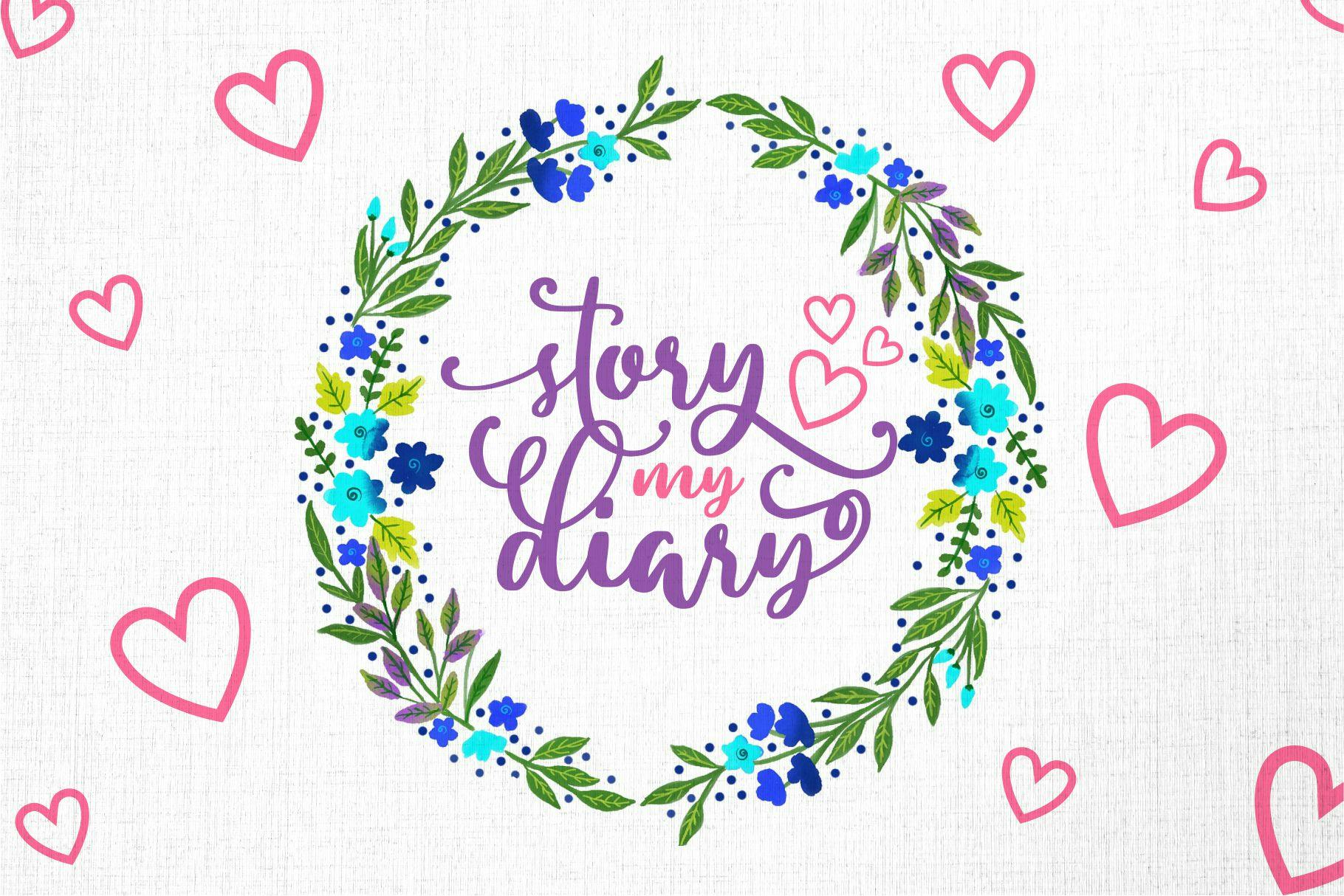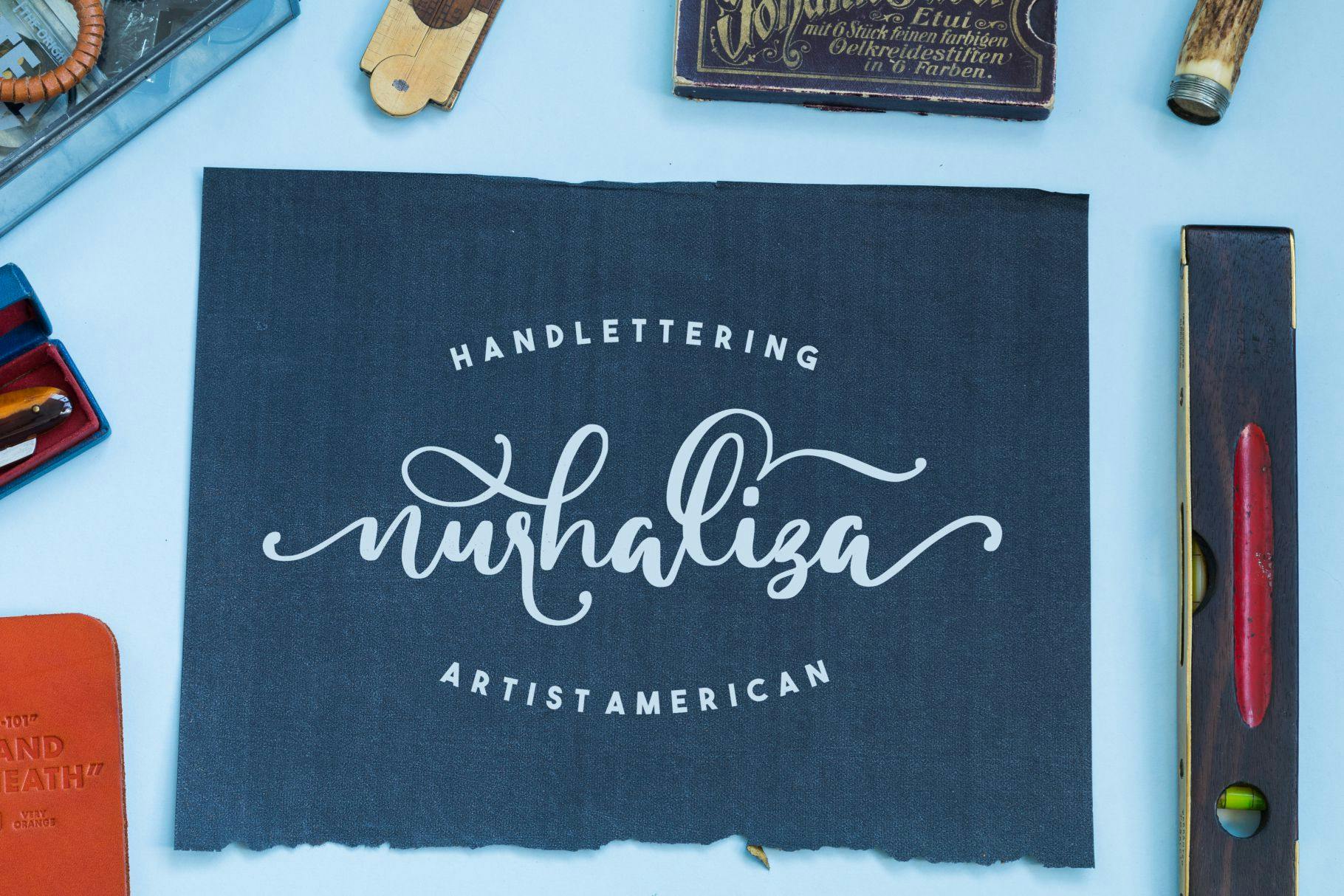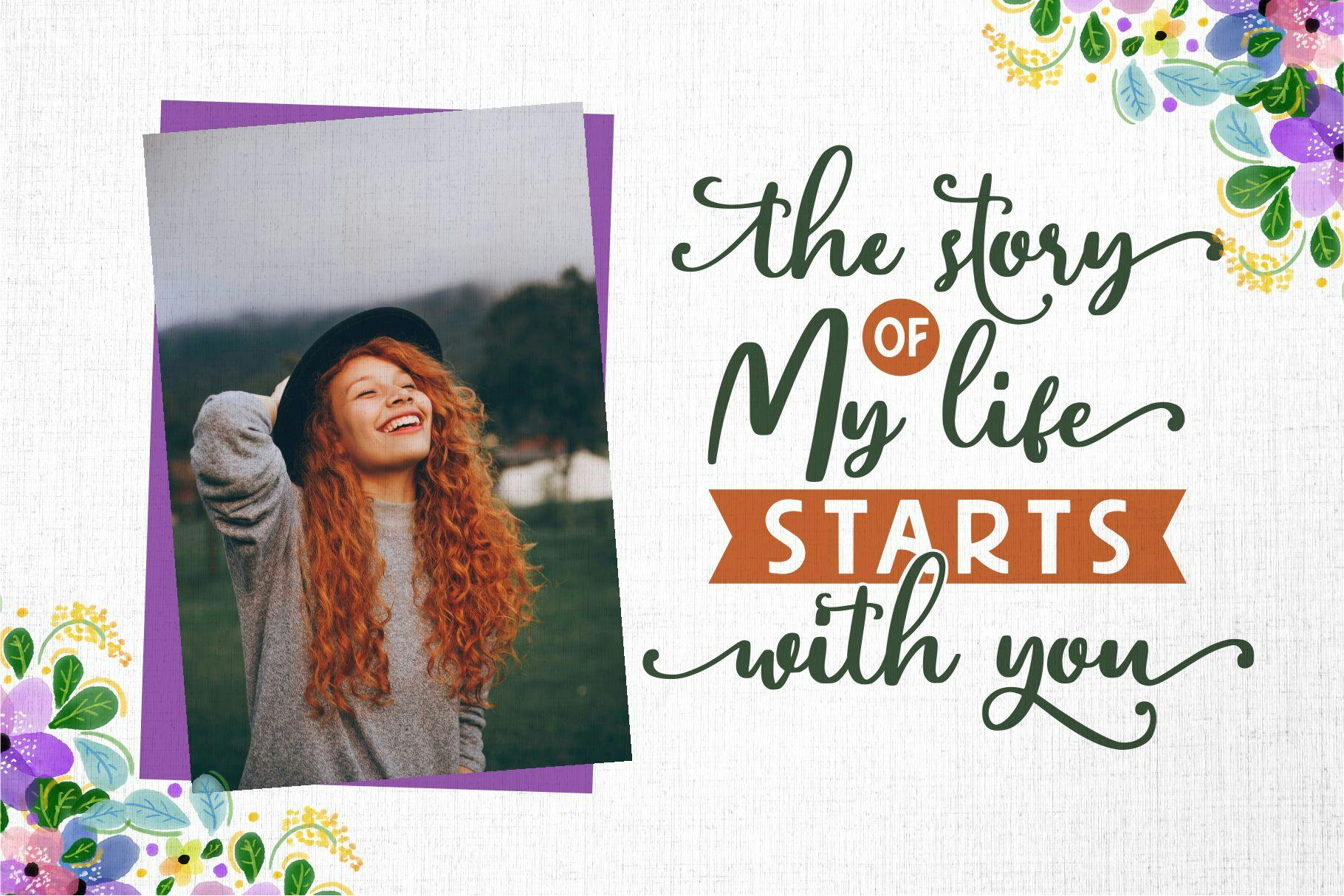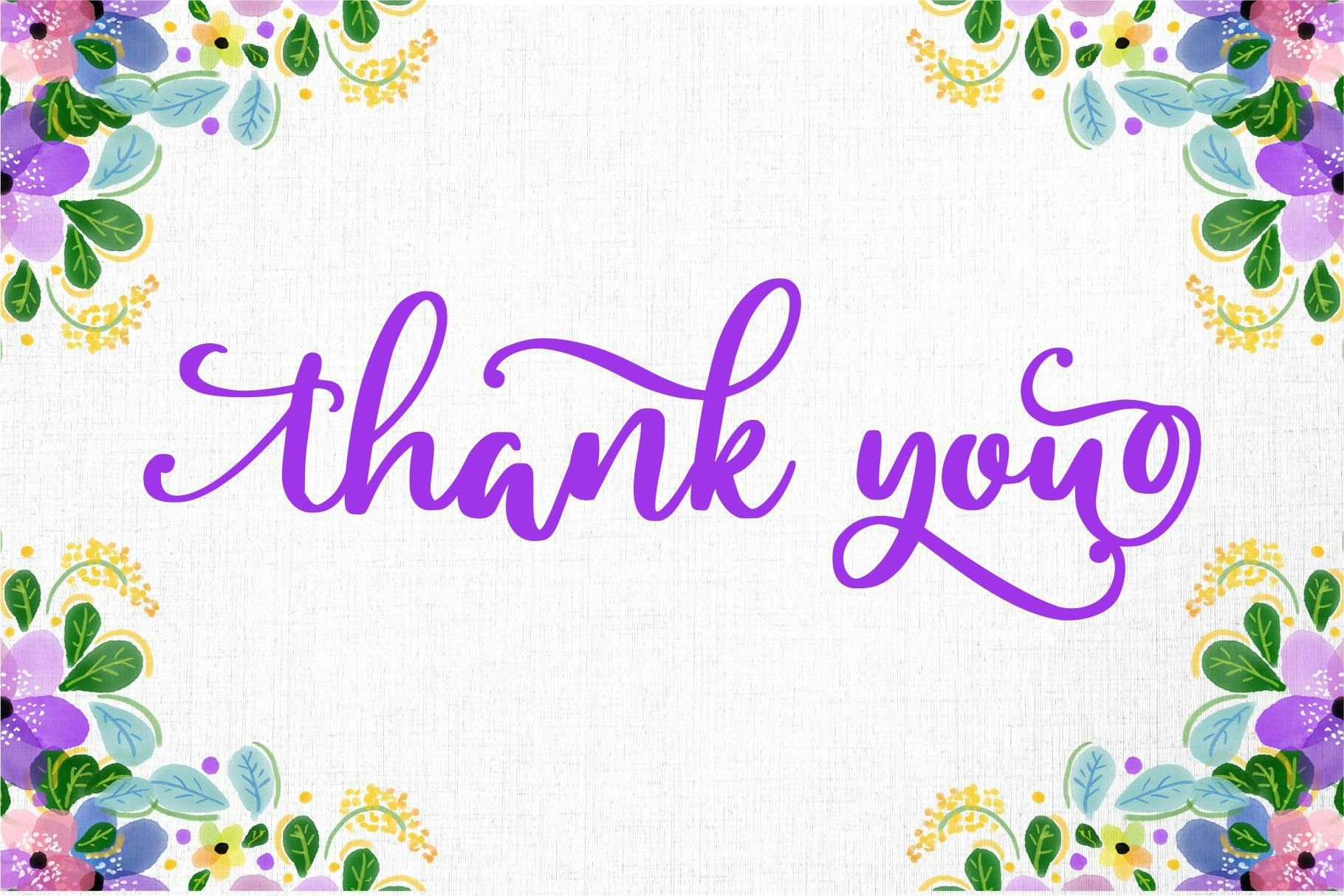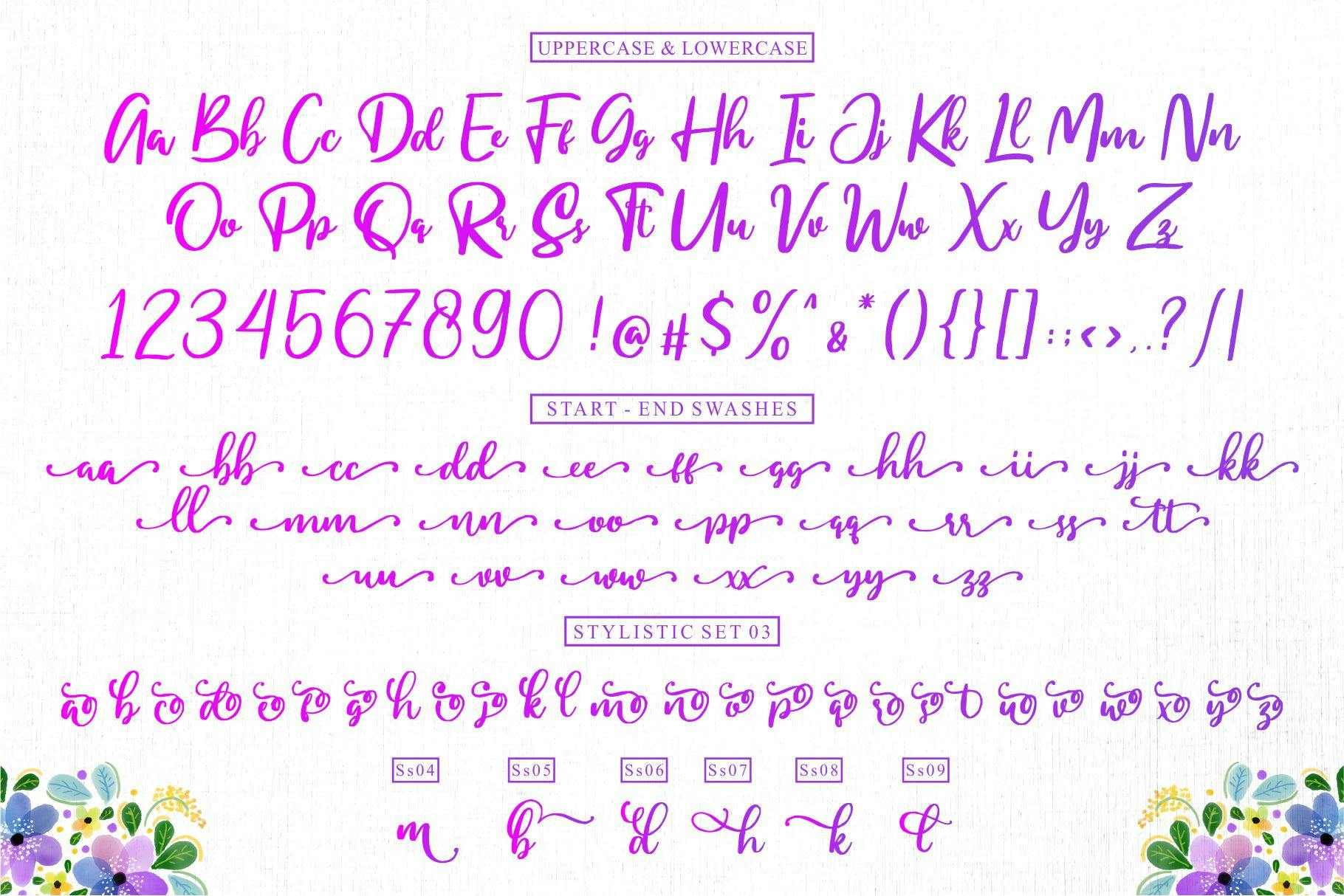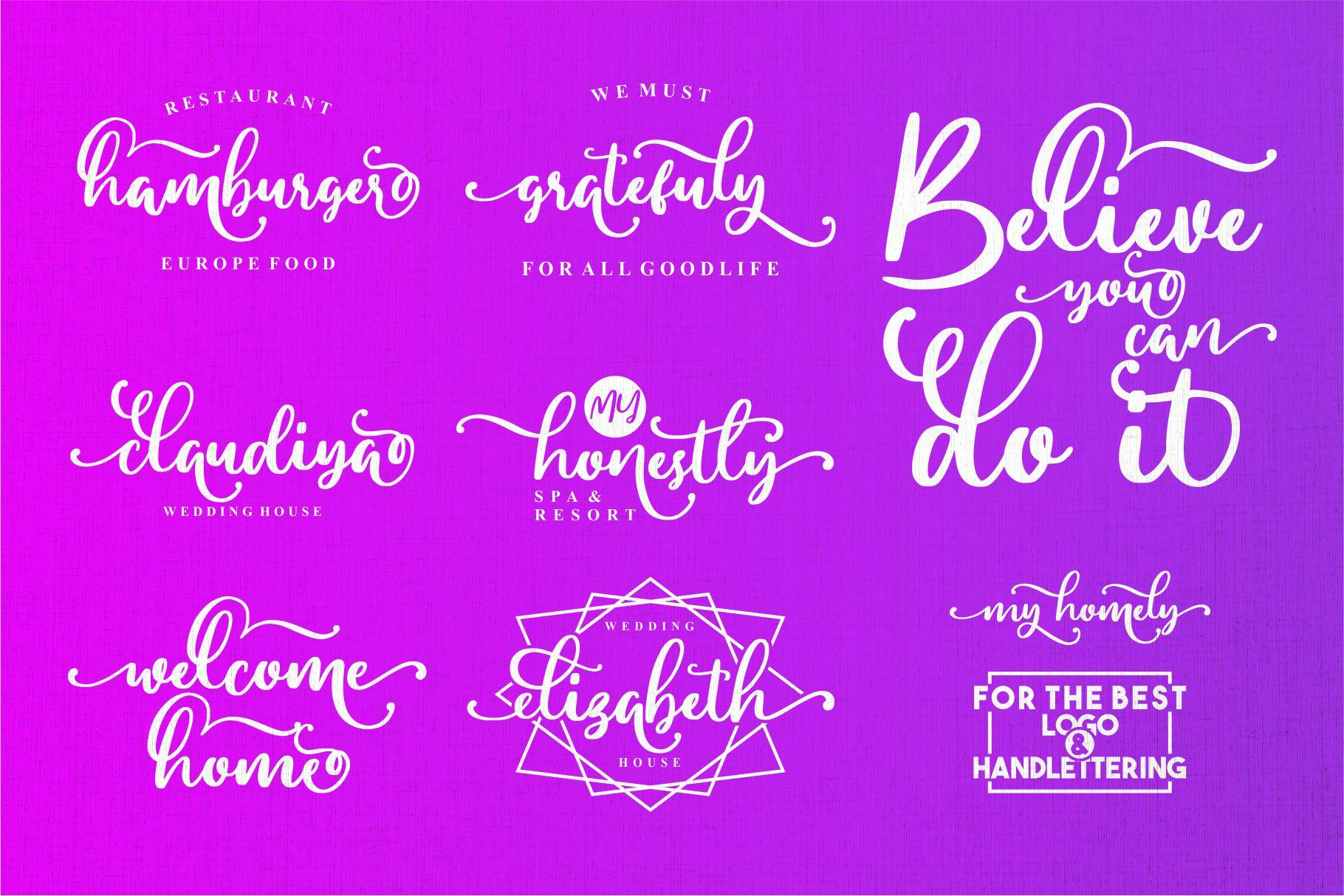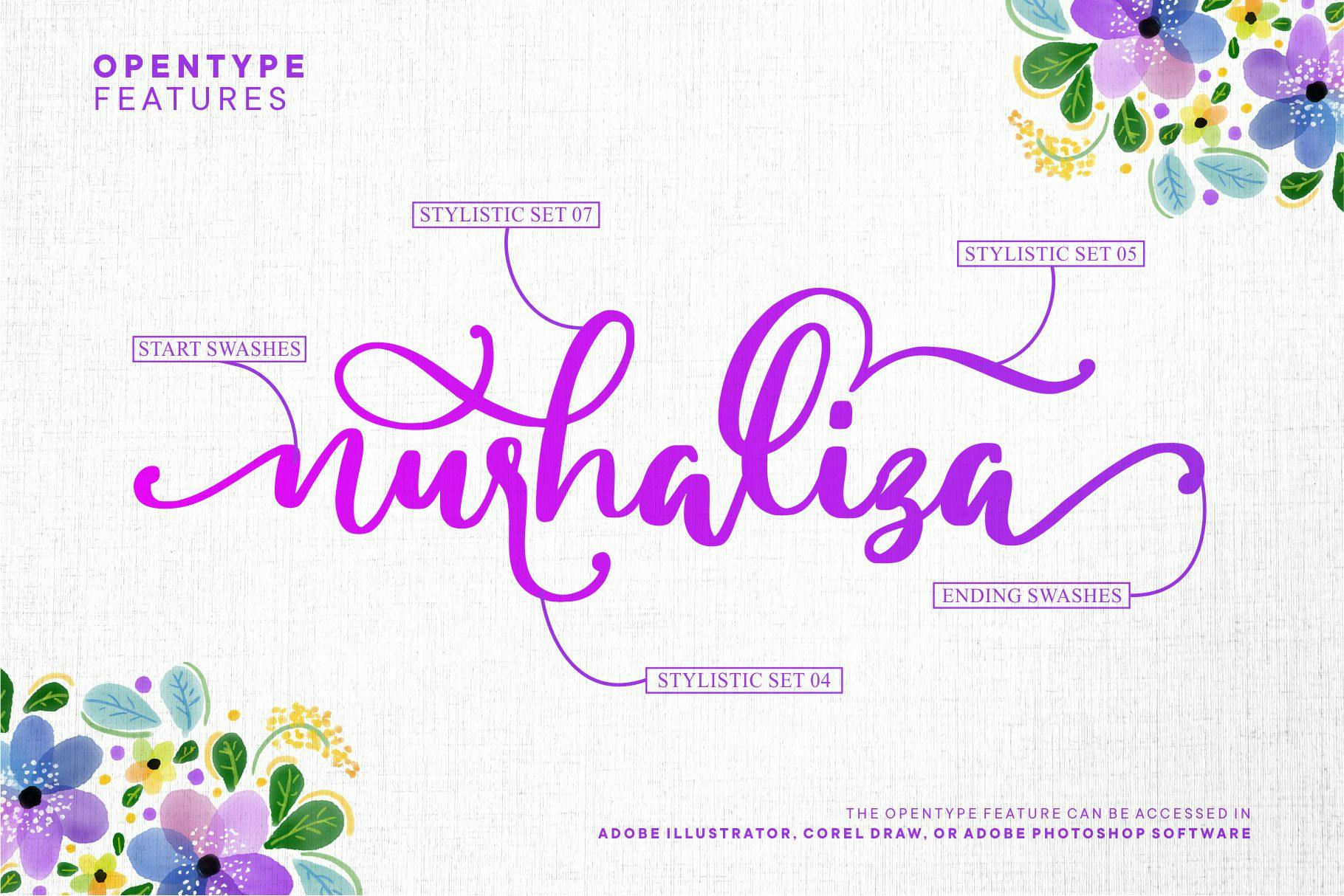
My Homelly Handlettering Font
فونت دست‌نویسی My Homely با طراحی زیبا و خاص، مناسب برای پروژه‌های مختلف.
معرفی: My Homely
فونت My Homely یک فونت زیبا و دست‌نویسی است که با استفاده از بسیاری از تزئینات در حروف ابتدایی و انتهایی طراحی شده است. این فونت شامل مجموعه کاملی از حروف کوچک با تزئینات قلبی، اعداد و نشانه‌گذاری‌ها می‌باشد. همچنین شامل لیگاتورها و مجموعه‌های سبک تا ۹ گزینه است. این فونت برای دعوت‌نامه‌ها، مونوگرام‌ها، عروسی، مد، برندینگ، لیبل یا لوگوتایپ بسیار مناسب است.
• لیگاتور و مجموعه‌های سبک
• بسیار مناسب برای برندینگ، لوگوتایپ، نامه‌نویسی، دعوت‌نامه‌ها یا برندینگ مد.